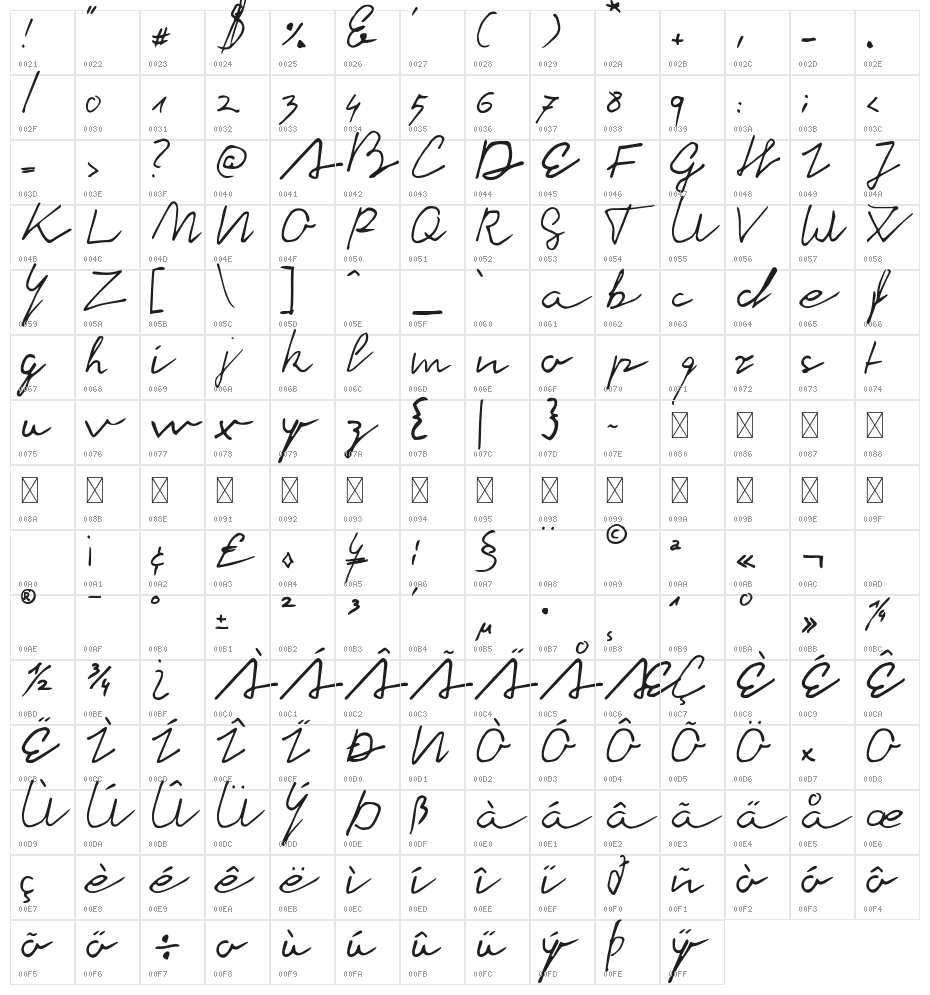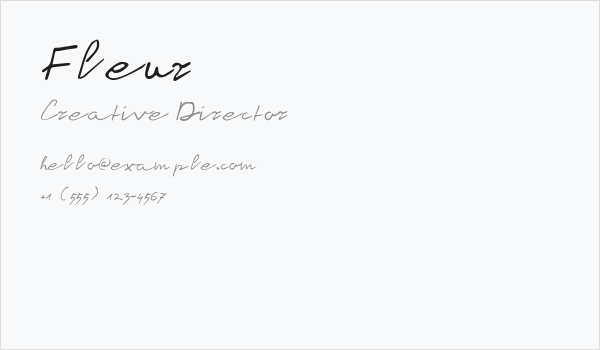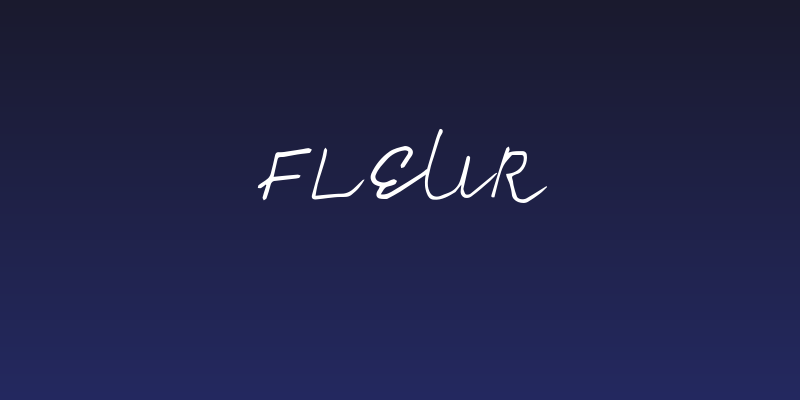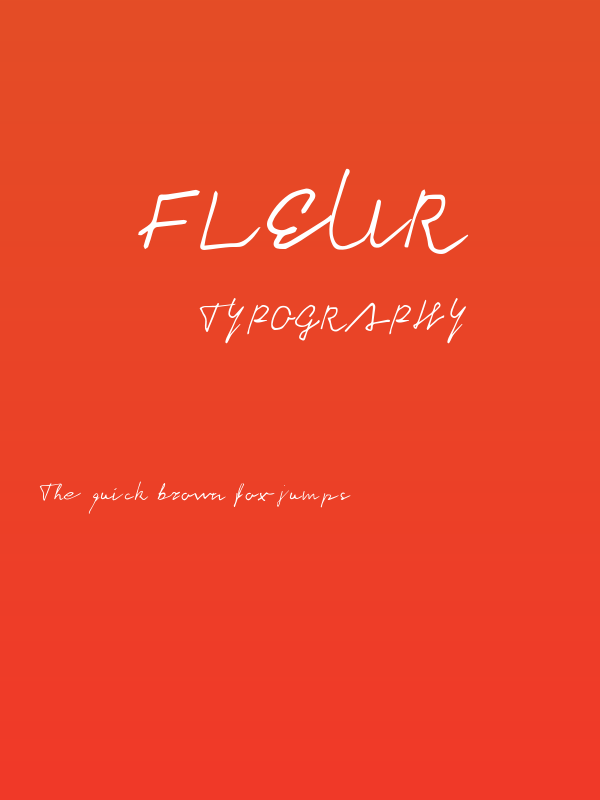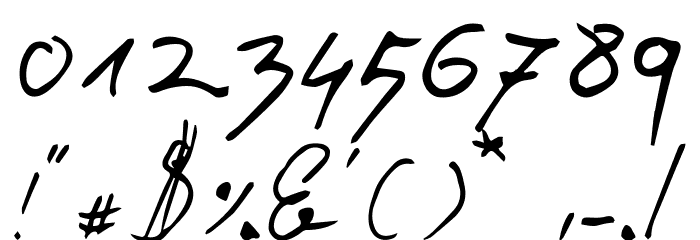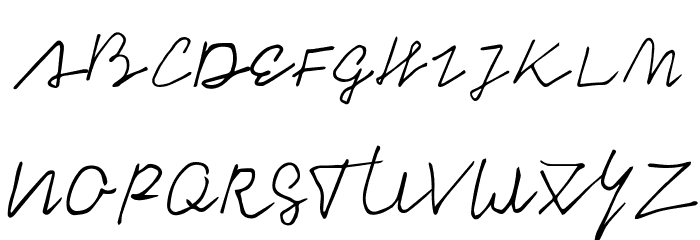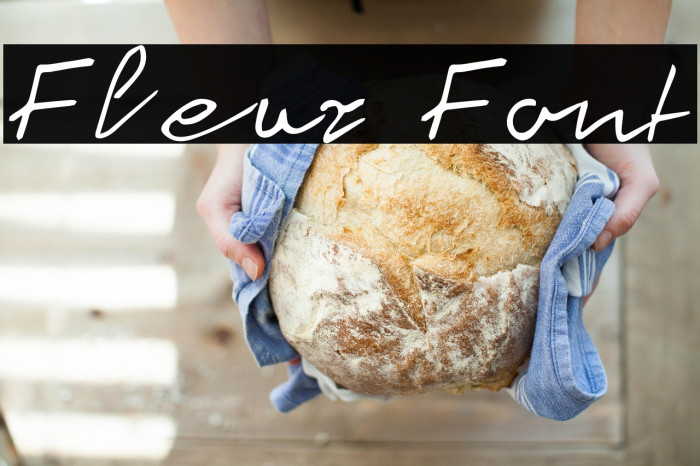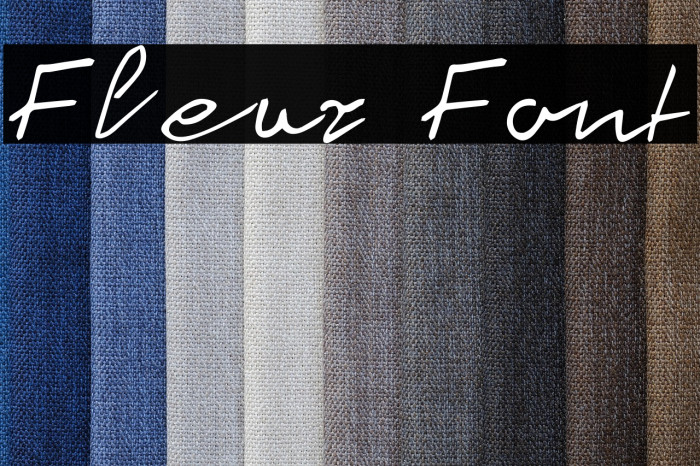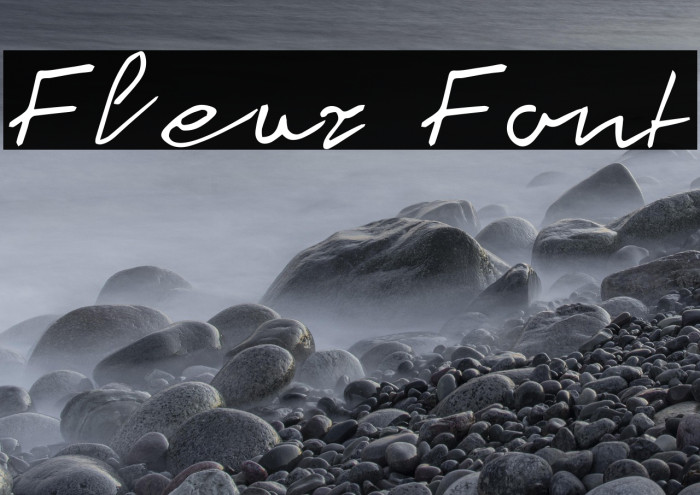
Fleur Font
| Cas d'utilisation | Logos, Invitations, Greeting Cards |
| Projets proposés | Ideal for personal invitations, greeting cards, and creative projects that require a personal touch. |